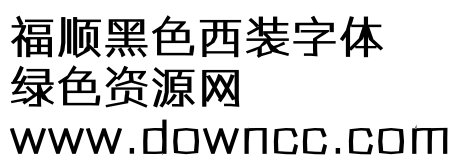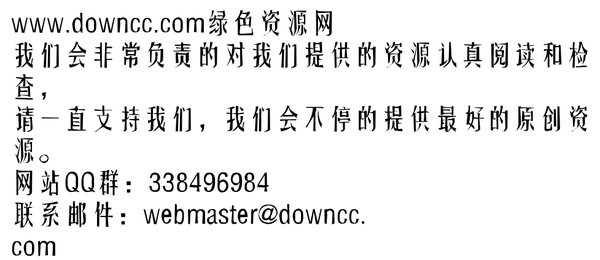
福順黑色西裝
福順黑色西裝字體給人隨性而嚴(yán)謹(jǐn)、高端而落拓的男性魅力,讓你的文字變得剛硬起來(lái),而一些字形的優(yōu)化也讓字里行間充滿(mǎn)多重驚喜!綠色資源網(wǎng)今日推薦!
福順黑色西裝體字體特色
福順黑色西裝獨(dú)辟蹊徑,賦予字體成熟男性的魅力,充斥在字里行間中,有著瀟灑而穩(wěn)重、利落而灑脫的藝術(shù)氣息,可以廣泛運(yùn)用在海報(bào)設(shè)計(jì)、藝術(shù)策劃、文字排版等諸多領(lǐng)域!
福順字體說(shuō)明
福順系列是產(chǎn)量比較高的藝術(shù)字體,打造不同尋常的特色書(shū)法,讓你的平面設(shè)計(jì)與眾不同,每一個(gè)字體都有不一樣的藝術(shù)魅力,讓使用的行業(yè)更加多變,無(wú)論是廣告創(chuàng)意還是印刷排版都很試用!